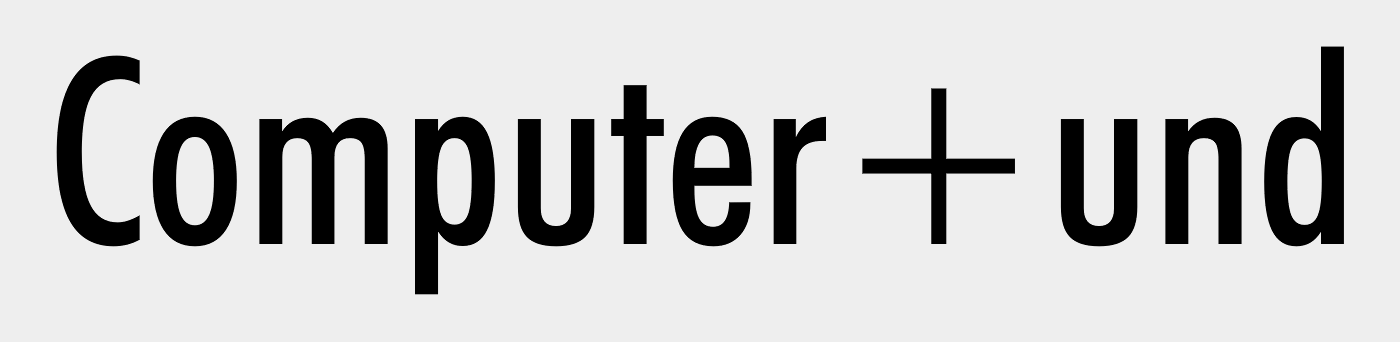
Welche Schriftart ist aus dem Bild abgebildet?
Ich habe das Problem, dass ich nicht heraus finden kann um welche Schriftart es sich auf einer Grafik handelt. Die bekannten Webseiten liefern alle viele verschiedene Ergebnisse, so dass ich sehr verunsichert bin.
Könntet ihr euch die Schriftart bitte mal anschauen und mir (falls ihr es heraus finden könnt) mitteilen um welche Font es sich handelt ?
Sie Sieht bisschen wie Futura bzw. ein zusammen gezogenes Arial aus. Aber ich würde es halt gerne genau wissen ;-)
vielen Dank für die super Antworten!!!!! Wusste nicht, dass es mit nur zwei Wörtern schwerer ist, die Font zu ermitteln. Sorry! Hier mal ein paar Wörter mehr, damit ihr es noch besser beurteilen könnt :-)
Sorry, I didnt know that its harder to determine the font when you see only two words. Here are some more words, so its easier to find the correct font.
Naja, es gibt bestimmte Buchstaben, die oft sehr charakteristisch für eine Schrift sind. Oft sind das z.B. a oder g. Aber dein zweites Beispiel erhärtet den Verdacht, dass es eine Futura ist, meines Erachtens.
Wenn Du Deinen Text zum Beispiel in den Editor von MyFonts fütterst und dann die in Frage kommenden Schnitte der verschiedenen Futuras durchklickst, dann solltest Du da eigentlich recht schnell zu einem Ergebnis kommen. Und weiter oben wird bereits die Futura medium condensed vorgeschlagen – damit hast Du ja schon einen ganz exakten Hinweis – soooo viele Futuras sind es ja dann zum Glück auch wieder nicht.  ;-)
Du meinst, superheld, ob es eine Futura von Bitstream, Linotype, Berthold oder wem auch immer ist? Das dürfte allerdings sehr sehr schwierig herauszufinden sein. Ist in deinem Fall die exakte Foundry tatsächlich so wichtig?
Ist in deinem Fall die exakte Foundry tatsächlich so wichtig?
Es gibt ja vermutlich sowieso nur entweder die Art von Kunden, denen es egal ist, welche Futura verwendet wird, oder diejenigen, denen es nicht egal ist, die dann aber eine professionell geführte Werbeabteilung haben, die einem sagen kann, welche Futura sie gern hätten.
Lukas: Ich wollte halt nur genau wissen welche Futura es ist. Die Auswahl an Futura Schrifarten scheint ja riesig zu sein. Ich finde auch, dass es wie eine Futura Medium Condensed aussieht, nur man weis es halt nicht genau :-) ... Würde es halt gerne genauer wissen . Der Hersteller ist mir nciht wichtig. Würde nur gerne wissen welche Futura das ist :-)
Eigeninitiative hilft bei solch einer Fragestellung ja auch manchmal weiter …  ;-)
Wie oben bereits beschrieben: Du kannst ganz einfach – zum Beispiel bei MyFonts – eine Zeile Deines Textes in den Textgenerator eingeben und dann alle dort vorhandenen Futura-Medium-condensed-Schnitte durchspielen. Von jeder Variante machst Du Dir vom Testtext einen Screenshot. Anschließend setzt Du Deinen Beispielsatz und die Screenshot-Zeilen untereinander auf ein Blatt und vergleichst. Dann dürftest Du Deinen Schnitt finden. Oder aber sie sehen alle gleich aus und dann spielt es wirklich keine Rolle, für welchen Hersteller Du Dich entscheidest. Dann solltest Du einfach schauen, was an unterschiedlichen Features die einzelnen Angebote noch so bereithalten und was sie kosten – und dementsprechend Deine Wahl treffen.
Kathrin: Danke für die Nachricht!! Denkst du aber, dass es sicher eine Futura Medium Condensed ist ??